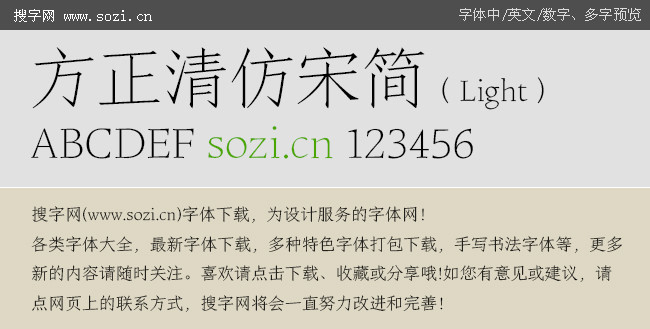
方正清仿宋簡(jiǎn)Light
搜字網(wǎng)提供一款方正清仿宋字體簡(jiǎn)中文字體下載,清仿宋字體創(chuàng)作吸收結(jié)合傳統(tǒng)仿宋和聚珍仿宋的特點(diǎn)所創(chuàng)制的新仿宋字體。字面寬博方正,具有時(shí)代感;筆畫清晰明確,有雕刻之硬朗風(fēng)范。給人一種清凈、明朗、安靜的感受。適合正文及小標(biāo)題使用。